Olá, pessoal! Quem aí nunca sonhou em ter um site que realmente se destaca, com aquela identidade visual que grita “sou eu” em cada detalhe? Sei bem como é essa vontade de fugir do básico e dar um toque único ao nosso espaço digital.
Por muito tempo, eu mesma quebrei a cabeça tentando entender como trazer aquela fonte linda que vi em um design para o meu próprio blog, sem que ele ficasse lento ou bagunçado.
É um desafio e tanto, não é? A verdade é que a escolha da fonte certa vai muito além de uma simples questão estética; ela é a voz da sua marca, o primeiro impacto visual que seu visitante tem.
E com as tendências atuais, como as fontes variáveis e a crescente preocupação com a experiência do usuário e a otimização para motores de busca, aplicar fontes personalizadas de forma inteligente se tornou essencial.
Eu já testei de tudo, e posso dizer que, quando bem feito, o resultado é transformador. Se você está cansado de ver seu site com a mesma cara de sempre e quer dar um verdadeiro “up” na sua presença online, garantindo que ele seja rápido, bonito e fácil de encontrar, então você chegou ao lugar certo.
Vamos descobrir juntos todos os segredos para aplicar fontes personalizadas no seu site e fazer com que ele brilhe!
A Voz do Seu Site: Por Que a Fonte É Tão Essencial?
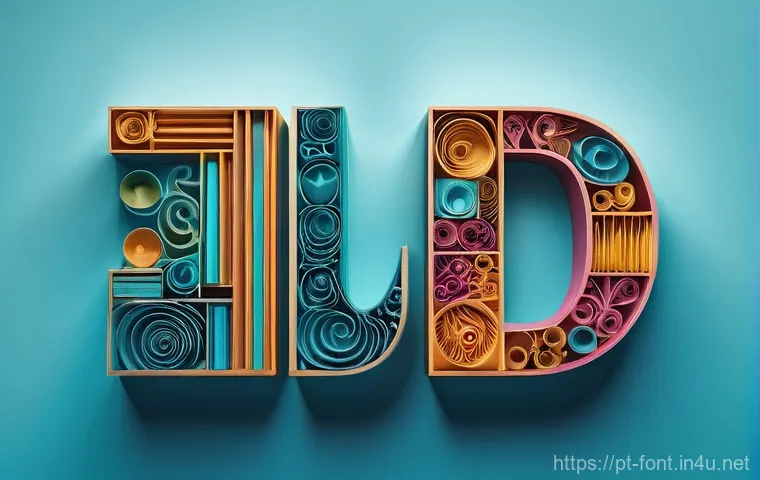
Gente, vamos combinar: a primeira impressão é a que fica, e no mundo digital, isso é ainda mais verdade! Sabe quando a gente entra num site e de cara já sente que ele tem a nossa cara, ou o contrário, que parece genérico e sem graça? Pois é, grande parte dessa sensação vem da fonte que o site usa. Não é só uma questão de “achar bonito”; a tipografia é a identidade, a alma do seu espaço online. Eu mesma, no início da minha jornada, focava tanto no conteúdo que acabava negligenciando esse detalhe crucial. Achava que qualquer fonte padrão servia, mas a verdade é que isso é um erro enorme! Pense comigo: a forma como as letras se apresentam pode transmitir seriedade, leveza, inovação ou tradição. É como a roupa que a gente escolhe para uma ocasião especial. Você não usaria um fato e gravata para ir à praia, certo? Da mesma forma, a fonte precisa estar alinhada com a mensagem e o público do seu blog. Uma fonte mal escolhida pode tornar a leitura cansativa, afastar visitantes e até mesmo fazer com que seu conteúdo, por melhor que seja, pareça menos profissional. Acreditem, já perdi algumas horas de sono tentando achar a combinação perfeita para o meu blog, e cada segundo valeu a pena. A diferença na taxa de permanência dos meus visitantes foi brutal depois que comecei a encarar a escolha da fonte como uma parte estratégica do meu branding. É o seu cartão de visitas visual, o sussurro que diz “olá, eu sou único” antes mesmo de o seu leitor digerir a primeira palavra.
Mais do que Estética: O Impacto na Legibilidade
Muitas vezes, a gente se apaixona por uma fonte superdiferente e esquece do principal: ela é legível? De que adianta ter a fonte mais estilosa do mundo se o seu leitor precisa forçar a vista para entender o que está escrito? A legibilidade é rainha, meus amigos! Eu já caí nessa armadilha de escolher uma fonte superornamentada para títulos, pensando que ia arrasar, mas percebi nos comentários e nas minhas análises que as pessoas estavam se cansando. Ninguém gosta de decifrar um texto. Precisamos pensar na experiência do usuário em primeiro lugar. Uma boa fonte é aquela que permite que o olho deslize pelo texto sem esforço, que não causa fadiga visual, especialmente em blocos grandes de conteúdo. E isso vale para todos os dispositivos! Aquela fonte linda no computador pode virar um borrão no telemóvel. Por isso, ao escolher, sempre teste em diferentes tamanhos e plataformas. Eu tenho um checklist mental que uso: consigo ler confortavelmente por 5 minutos? E por 10? Se a resposta for sim, então estamos no caminho certo. Uma tipografia bem escolhida melhora a experiência de leitura, aumenta o tempo de permanência no site e, consequentemente, sinaliza para os motores de busca que seu conteúdo é valioso.
Alinhando a Fonte com a Personalidade da Sua Marca
Seu site tem uma história para contar, uma personalidade para expressar. A fonte é um dos narradores mais poderosos dessa história. É ela que ajuda a definir se sua marca é divertida, séria, moderna, clássica, ou o que quer que seja. Pensem nos grandes players do mercado. Eles investem pesado na identidade visual, e a tipografia é um pilar disso. Eu me lembro de um projeto que fiz para um cliente da área de design, e ele queria algo que transpirasse criatividade e inovação. Começamos com as fontes padrão e o resultado era… meh. Sem alma! Quando introduzimos uma fonte personalizada, mais geométrica e com um toque artístico, o site simplesmente ganhou vida. Parecia outra coisa! A percepção do público mudou radicalmente. É como encontrar a sua voz única no meio de um coro. A fonte certa vai reforçar a mensagem da sua marca e criar uma conexão emocional com seu público. Ela é um elemento não verbal que fala muito sobre quem você é e o que você oferece. Não subestimem o poder de uma escolha tipográfica consciente; ela pode ser o segredo para se destacar em um mar de conteúdos.
Onde Encontrar Fontes Personalizadas para Chamar de Suas?
Então, a gente já sabe que escolher a fonte certa é um passo gigante para ter um site com a nossa cara, não é? Mas a grande questão que surge logo em seguida é: onde a gente encontra essas belezuras personalizadas? Não se preocupem, porque hoje em dia temos um arsenal de opções, e muitas delas são gratuitas ou de custo bem acessível. Eu lembro que no começo era um desafio, tinha medo de usar fontes sem licença e acabar tendo problemas. Mas com o tempo, descobri plataformas que são verdadeiros tesouros. O Google Fonts, por exemplo, é meu queridinho para começar. A variedade é enorme, e o melhor: é tudo de graça e super fácil de implementar. Tem desde as fontes mais clássicas até umas mais ousadas. Além disso, a otimização delas já vem pronta, o que ajuda muito na performance do site. Mas se você busca algo mais exclusivo, com um toque realmente profissional, existem sites como o Adobe Fonts (se você já assina a Creative Cloud, é um bônus e tanto!), MyFonts e Font Squirrel. Cada um tem suas particularidades. No Font Squirrel, por exemplo, você encontra muitas fontes gratuitas para uso comercial. A minha dica é explorar, testar, não ter medo de fuçar! Passe um tempo navegando, fazendo combinações, e você vai se surpreender com o que pode descobrir. O importante é sempre verificar a licença de uso para não ter dor de cabeça depois. Afinal, a gente quer brilhar com ética, certo?
Plataformas Gratuitas vs. Pagas: Qual Caminho Seguir?
Essa é uma pergunta que sempre me fazem: devo investir em fontes pagas ou as gratuitas dão conta do recado? A resposta, como quase tudo na vida, é: depende! Para a maioria dos blogs pessoais e até mesmo para muitos pequenos negócios, as fontes gratuitas de plataformas como o Google Fonts oferecem uma qualidade e variedade incríveis. Eu mesma usei por muito tempo só fontes do Google, e meu site sempre teve uma aparência super profissional. Elas são bem otimizadas, fáceis de usar e têm suporte para vários idiomas, o que é ótimo para quem pensa em expandir. No entanto, se você busca um diferencial competitivo muito forte, uma identidade visual super exclusiva ou precisa de uma fonte com características muito específicas (como fontes variáveis, que falaremos adiante), as plataformas pagas podem ser o seu melhor investimento. Sites como MyFonts, Fontspring ou Creative Market oferecem opções premium, muitas vezes desenhadas por designers renomados, que podem dar um toque de sofisticação e originalidade que as gratuitas talvez não consigam. A decisão final deve levar em conta seu orçamento, a exclusividade que você busca e o impacto que a fonte terá na percepção da sua marca. Já vi fontes pagas que realmente transformaram a imagem de um negócio, fazendo valer cada cêntimo investido. No final das contas, o importante é que a fonte escolhida cumpra seu propósito, seja gratuita ou não.
Licenças de Uso: Não Caia em Armadilhas!
Olha, essa parte é importantíssima e muita gente acaba esquecendo ou ignorando: as licenças de uso das fontes! Não é porque você achou uma fonte linda na internet que pode sair usando-a em tudo que é lugar. As fontes são softwares, e como qualquer software, têm suas regras de uso. A maioria das fontes gratuitas do Google Fonts, por exemplo, tem uma licença Open Font License (OFL), que permite o uso pessoal e comercial. Mas existem outras licenças que podem restringir o uso, por exemplo, apenas para projetos pessoais, ou exigir atribuição ao designer. Eu já vi casos de pessoas que usaram fontes sem verificar a licença e acabaram tendo que mudar todo o design do site depois de um aviso de copyright. Que dor de cabeça! Por isso, antes de se apaixonar por uma fonte e começar a implementá-la, dedique cinco minutinhos para ler a licença. Geralmente, essa informação está bem visível nas páginas de download ou nas plataformas. Se for uma fonte paga, a licença virá junto com a compra e pode especificar se o uso é para web, impressão, número de domínios, etc. Fiquem espertos! Um uso indevido pode trazer problemas legais e financeiros que a gente não quer nem de longe. Agir com responsabilidade é a melhor forma de garantir que seu site brilhe sem sustos.
Como Trazer as Fontes para o Seu Site: A Magia do CSS
Chegou a hora de colocar a mão na massa e fazer essas fontes maravilhosas aparecerem no seu site! Parece um bicho de sete cabeças, mas eu garanto que com um pouco de calma e as ferramentas certas, a gente consegue. A principal ferramenta aqui é o CSS, a linguagem que dá estilo ao nosso site. Existem basicamente duas formas mais comuns de aplicar fontes personalizadas: importando-as de um serviço como o Google Fonts, ou hospedando-as diretamente no seu servidor. Para quem está começando, a opção do Google Fonts é um espetáculo! É super simples: você escolhe a fonte, o Google te dá um código para colar no